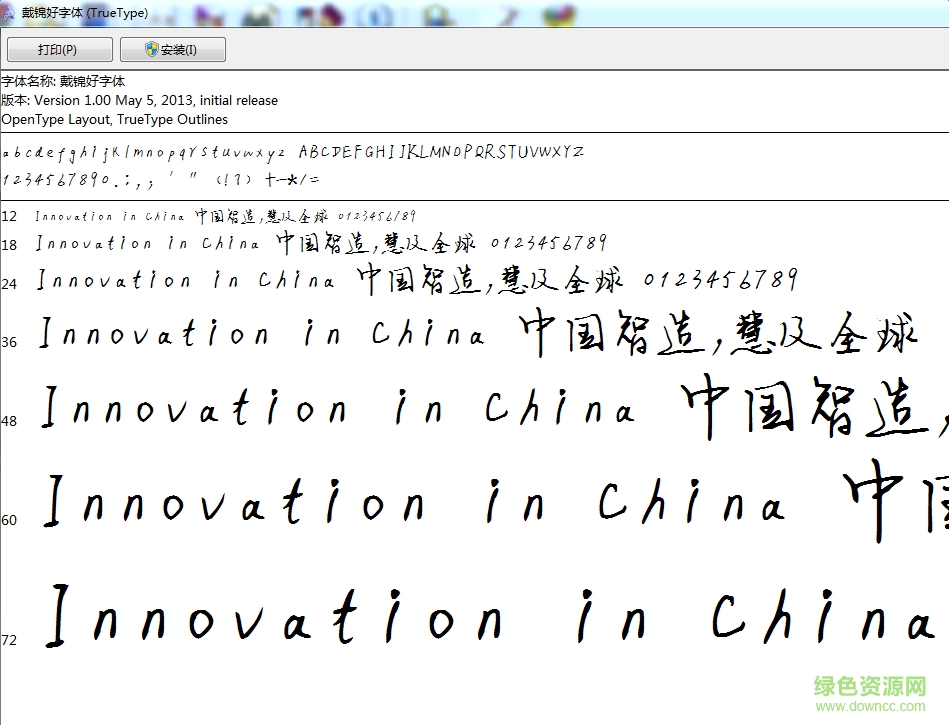
戴錦好字體x
戴錦好字體是一款時尚酷炫風(fēng)格字體軟件,戴錦好體筆畫隨意灑脫,卻別有一番韻味,介于楷書與行書之間,創(chuàng)意獨特,深受廣大書法家喜愛,還有更多好看字體歡迎來綠色資源網(wǎng)下載體驗!
戴錦好字體是一款應(yīng)用于藝術(shù)設(shè)計方面的簡體中文字體,該字體筆畫粗壯,尾部的甩尾有力且有豐富的筆觸細(xì)節(jié),大字效果突出且引人注目;并且最大程度還原作者書寫字形,細(xì)節(jié)表現(xiàn)完整,且字庫完整,可以廣泛應(yīng)用于名片設(shè)計、新聞媒體、宣傳海報、ppt、影視制作以及內(nèi)容用字等領(lǐng)域。